かっこいい&おしゃれなデザイン英語フォント一覧【SF・スポーツ・今っぽい】
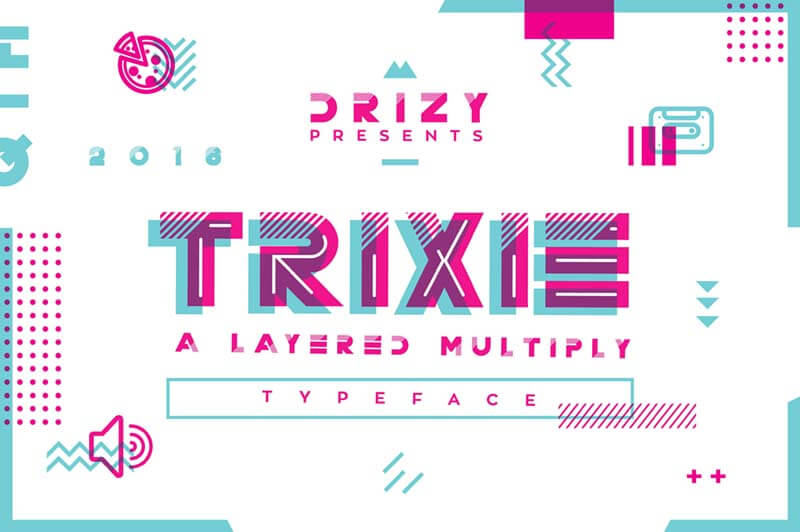
今回は今っぽい・SF・スポーツのクールな英文フォントを紹介します。
ここで紹介しているフォントを使えば、かっこよくて完成度の高いデザインが短時間でできあがりますよ。
かっこいい&おしゃれな英語無料フォント
無料フォント①:DELOGY – FREE DISPLAY FONT
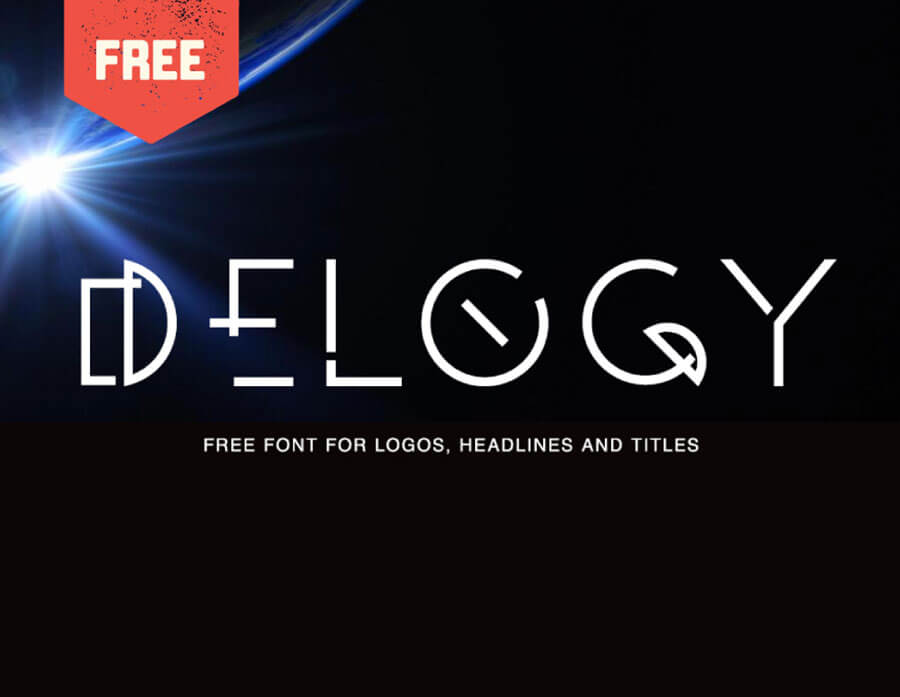
デザイン性が高く、タイトルや見出しなどで使いたいフォント。ロゴデザインにも使えそうですね。
無料フォント②:FACON – FREE ATHLETIC DISPLAY FONT
格闘技をはじめとしたスポーツ関連や少年向けのアニメなどと相性が良さそうなフォント。主張が強いので、ほかのフォントと組み合わせる時はシンプルなものを選ぶといいでしょう。
FACON – FREE ATHLETIC DISPLAY FONT
無料フォント③:FREE FAT FONT
極太で安定感があるフォント。画像のように派手な色と組み合わせたり、白黒でメリハリを出して使いたいですね。
無料フォント④:POTRA – FREE DISPLAY FONT
主に2本のラインとドットで構成された装飾性の高いフォント。使い方によってはかわいらしくも見えるので、幅広く使えそうです。
無料フォント⑤:MD TALL – FREE CONDENSED FONT
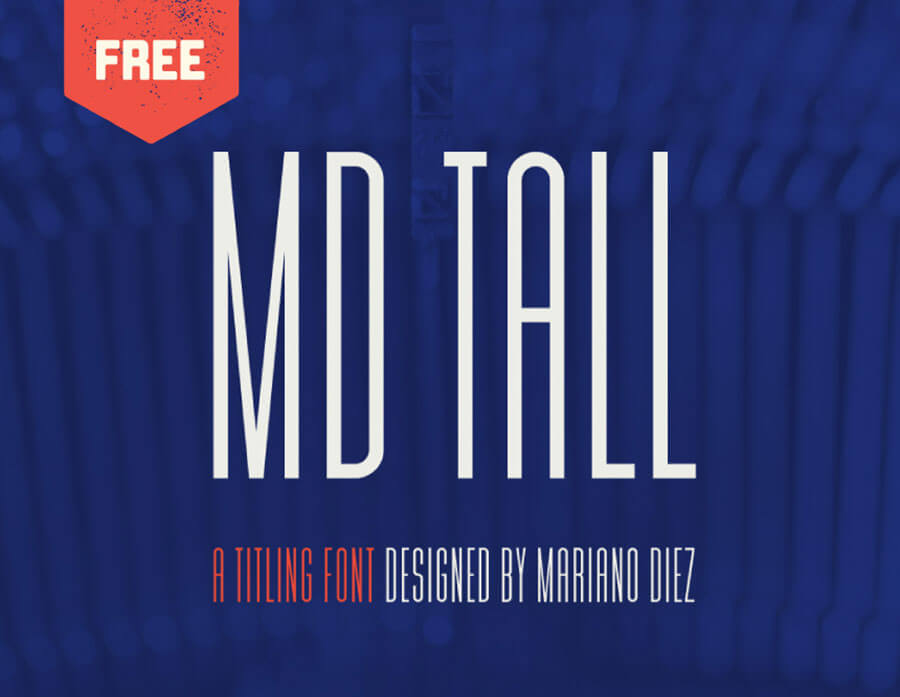
ウェイトが細くシャープな印象のフォント。クセがなく使いやすい書体なので、一つ持っておくと便利に使えますよ。
無料フォント⑥:ELALBA – FREE DISPLAY FONT
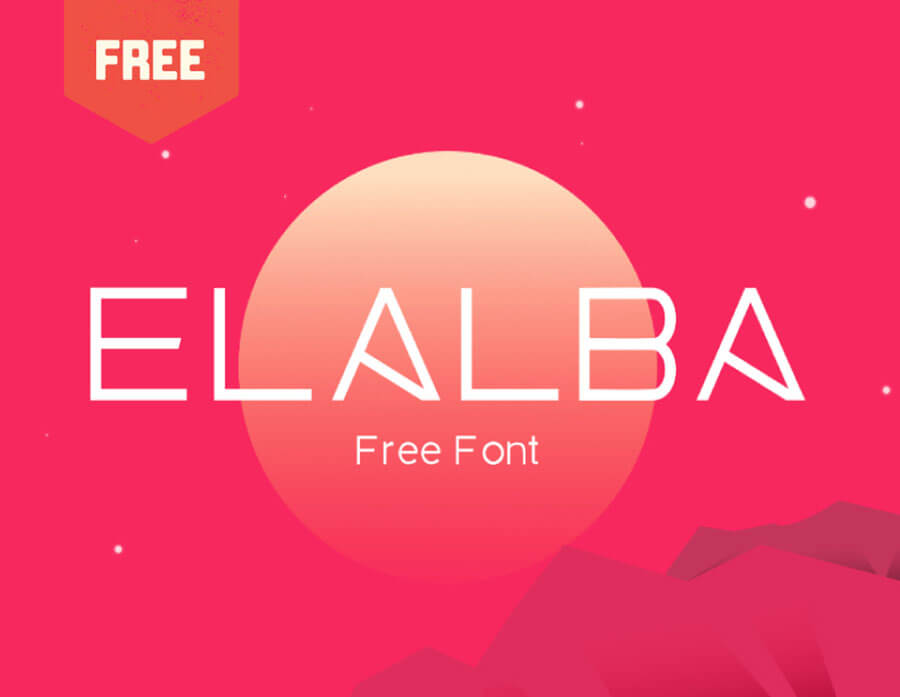
大文字のAやKがユニークなデザインのフォント。ベースはシンプルなので、小さくしても読みやすい書体です。
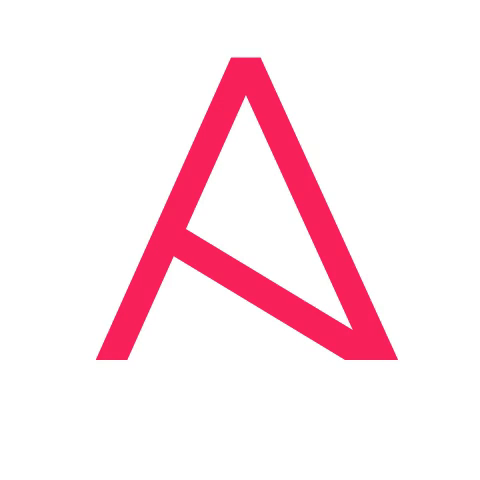
無料フォント⑦:APEX MK2 – FREE SANS SERIF FONT
無駄がないシャープな印象のフォント。ウェイト違いで3書体あり、小さくても大きくても読みやすくて万能です。
無料フォント⑧:QUANTUM – FREE FONT
斜めに入ったラインがユニークなフォント。数字にもラインが入っています。近未来的な雰囲気が魅力的な書体です。
かっこいい&今っぽさが演出できる英語フォント
Trixie | A Layered Multiply Typeface
これを使うだけですぐに今っぽい雰囲気のデザインができます!書体の組み合わせで幾通りもの表現ができるのもうれしいポイント。アイコンパックとフライヤー&ギフト券テンプレートもついてくるので、ダウンロードしたらすぐにデザインにとりかかれます。
Bank typeface
こちらも組み合わせること前提でデザインされたフォントセット。幾何学模様の背景12点もついてきますよ!
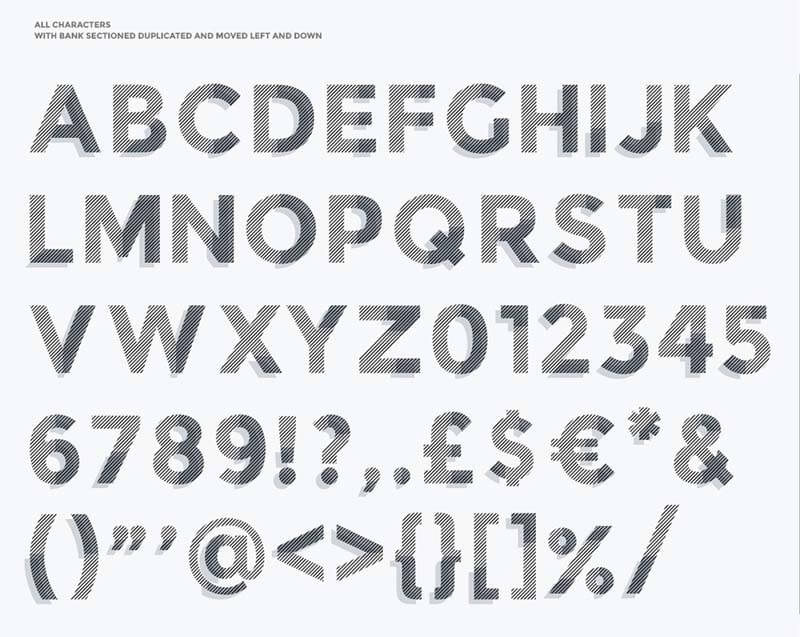
Argon Font (Full)
デザインのポイントとしてどん!と大きく使いたいフォントです。ロゴデザインにも使えそう。
かっこいいSF風英語フォント
SFっぽいフォントを紹介します。ロゴや見出しなどにも使えますよ。
Anurati Pro — typeface (2 weights)
異世界の言葉っぽい書体。長文には向きませんが、見出しにうまく使いたいフォントです。
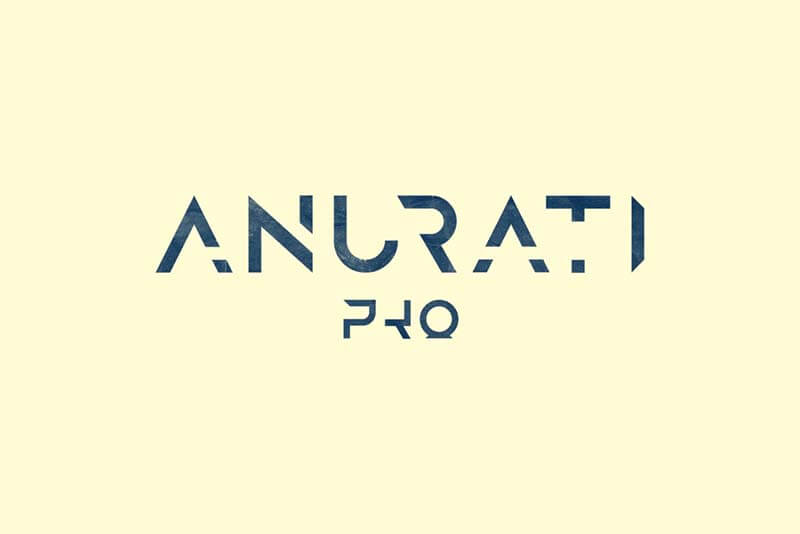
Teratur Typeface (3 Font)
こちらも宇宙っぽさが出ているフォント。丸みがある書体なので、冷たい印象にしたくないときに使うといいかも。
Kusanagi – Futuristic Font
シャープな部分とカーヴィな部分をうまく組み合わせたフォント。ある程度の長さの文章も問題なく読めます。
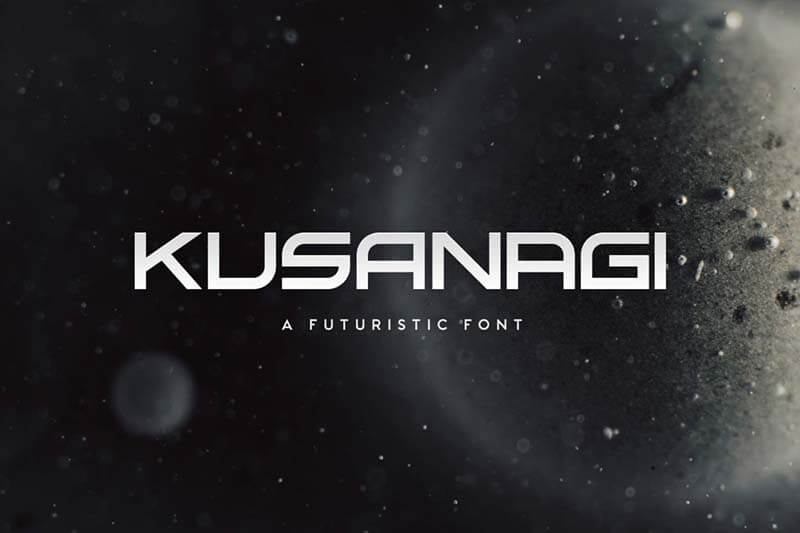
かっこいい&スポーツにぴったりのクール系英語フォント
スポーツチームやジムのロゴ作りに役立ちそうなクール系フォントを集めました。
Infield
雰囲気の異なる4書体のセット。組み合わせ次第で多様な表現ができますよ。
League – Display Typeface
野球チームのロゴで使われていそうな書体。イタリック体もあります。
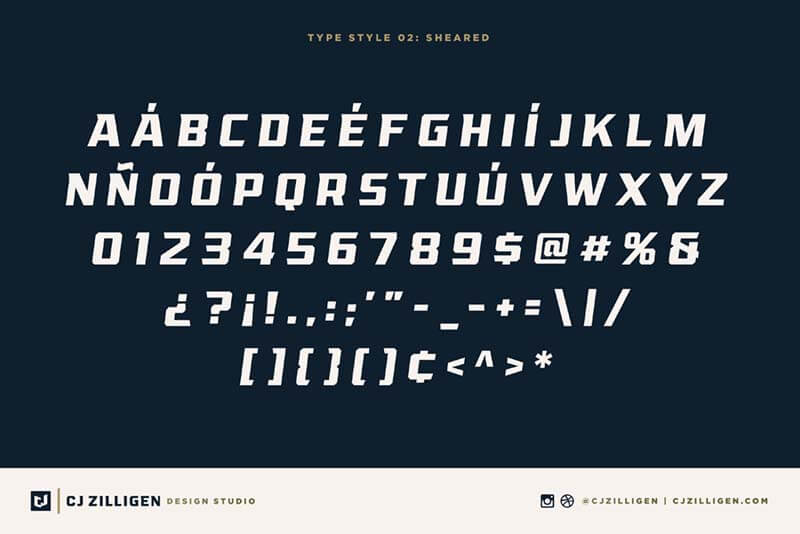
Redzone – The UFL Project
こちらもスポーツチームのロゴに使えそう。見出しに使えるカッコよさと、ある程度長い文章にも対応できる読みやすさをかねそなえた書体です。